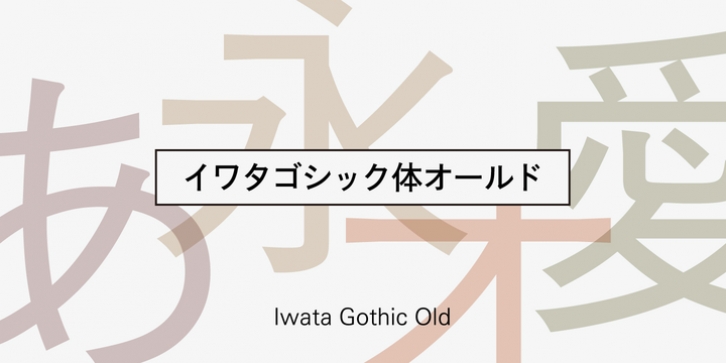
Iwata Gothic Old Std was published by IWATA. Iwata Gothic Old Std contains 6 styles and family package options.
æ´»å—æ›¸ä½“「岩田呉竹体ã€ã®ãƒ‡ã‚¶ã‚¤ãƒ³ã‚’引ãç¶™ãã€ä¼çµ±ã‚るゴシック体ã§ã™ã€‚
èµ·ç†ã€çµ‚ç†éƒ¨ã®æ´»å—特有ã®ã‚¢ã‚¯ã‚»ãƒ³ãƒˆãŒåЛ強ã•ã‚’ä¼ãˆã¾ã™ã€‚大見出ã—ã‹ã‚‰æœ¬æ–‡ã¾ã§å¹…広ã対応ã§ãã¾ã™ã€‚